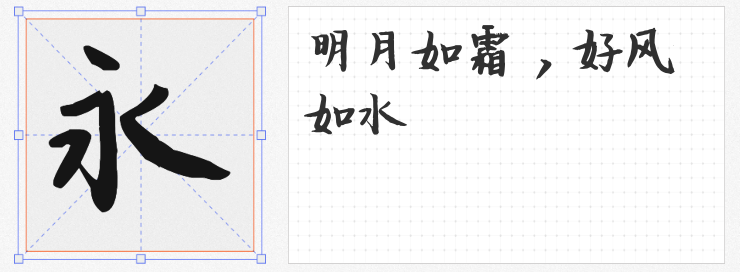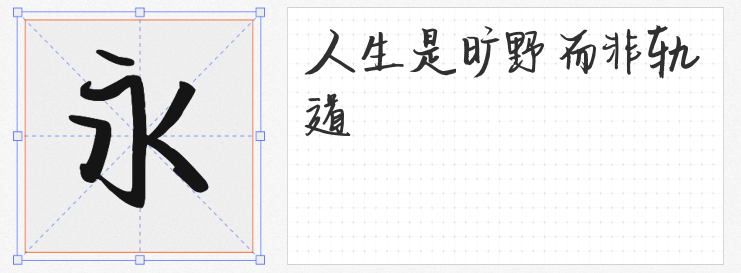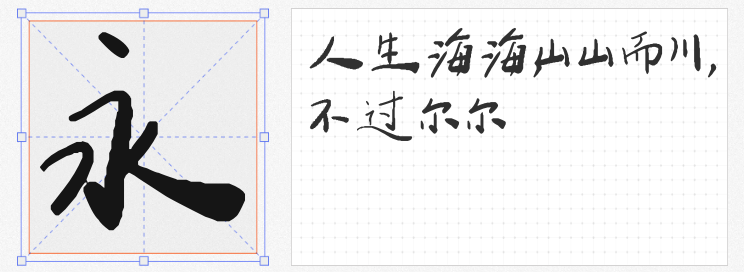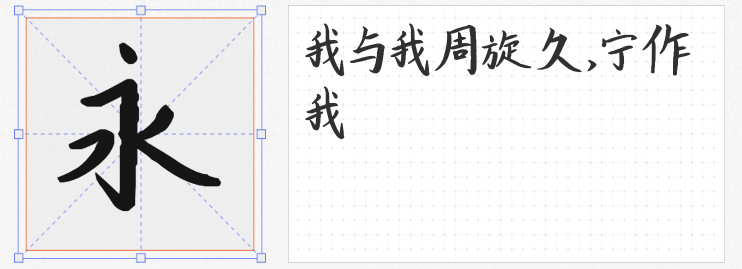
在数字设计日益追求个性化的今天,手写字体的独特韵味成为打破模板化视觉的关键利器。本文精选四款免费可商用的高质量手写字体,涵盖力量感、清新风、流畅韵律与端正雅致四大风格,助设计师轻松提升作品情感表达力。
1. 平方战狼体
以硬笔书写为根基,笔画如刀刻般苍劲有力,收笔处的连贯飞白赋予文字动态生命力。这款字体尤其适合运动品牌海报、游戏宣传等需要传递热血张力的场景,单字结构紧凑而富有节奏感,即便在小尺寸应用中依然能保持清晰辨识度,是打造视觉冲击力的利器。
2. 平方相思体
笔画粗细均匀如春日细雨,结构规整中透着灵动呼吸感。这款字体自带文艺滤镜,在美食包装、手账素材、女性品牌视觉中表现尤为出色。其克制而不失温度的设计语言,既能独立成为视觉焦点,也可与插画元素和谐共生,营造出轻盈治愈的视觉氛围。
3. 平方手书体
笔触粗细自然过渡,书写节奏感强烈,既有传统书法的韵律之美,又符合现代设计简洁需求。在海报标题、品牌Slogan等场景中,其流畅的笔画走向能自然引导视觉流动,特别适合文化类、教育类项目的视觉呈现,搭配水墨元素可瞬间提升格调。
4. 平方江南体
字形结构端庄如大家闺秀,笔触温润中暗藏筋骨,在保持手写自然感的同时兼具印刷体的规整性。这款字体堪称新中式设计的绝配,从茶饮包装到国风文创,从网页标题到书法字帖,其含蓄内敛的气质能完美承载东方文化意境。
这四款字体均通过精心数字化处理,在保留手写真实质感的同时,确保多场景应用的适配性。设计师可依据项目调性自由组合,让每个文字都成为传递品牌温度的视觉符号。